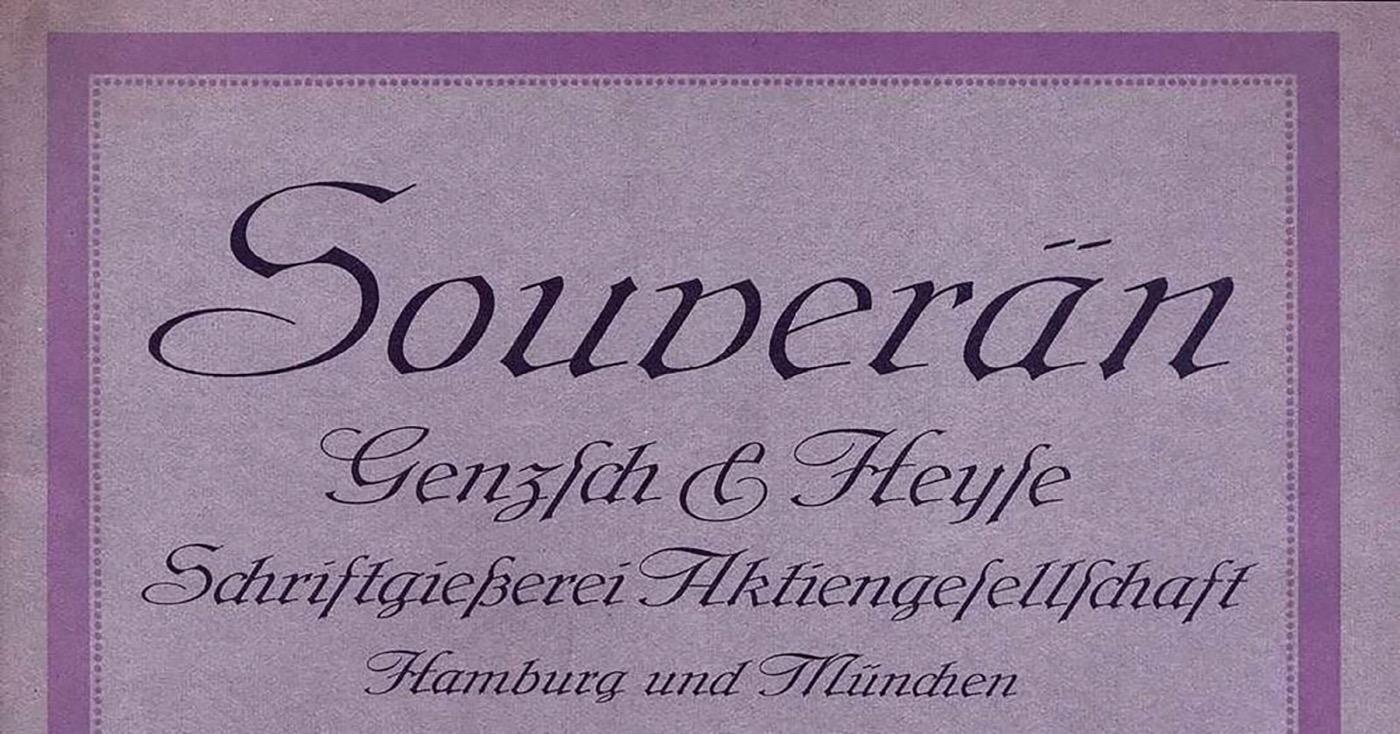
- 1913
- Antiqua Schreibschrift
Die Souverän ist eine unverbundene Schreibschrift von Albert Auspurg. Der 1913 bei Genzsch & Heyse erschienene Entwurf verbindet gestalterische Eigenschaften von Antiqua- und Frakturschriften.